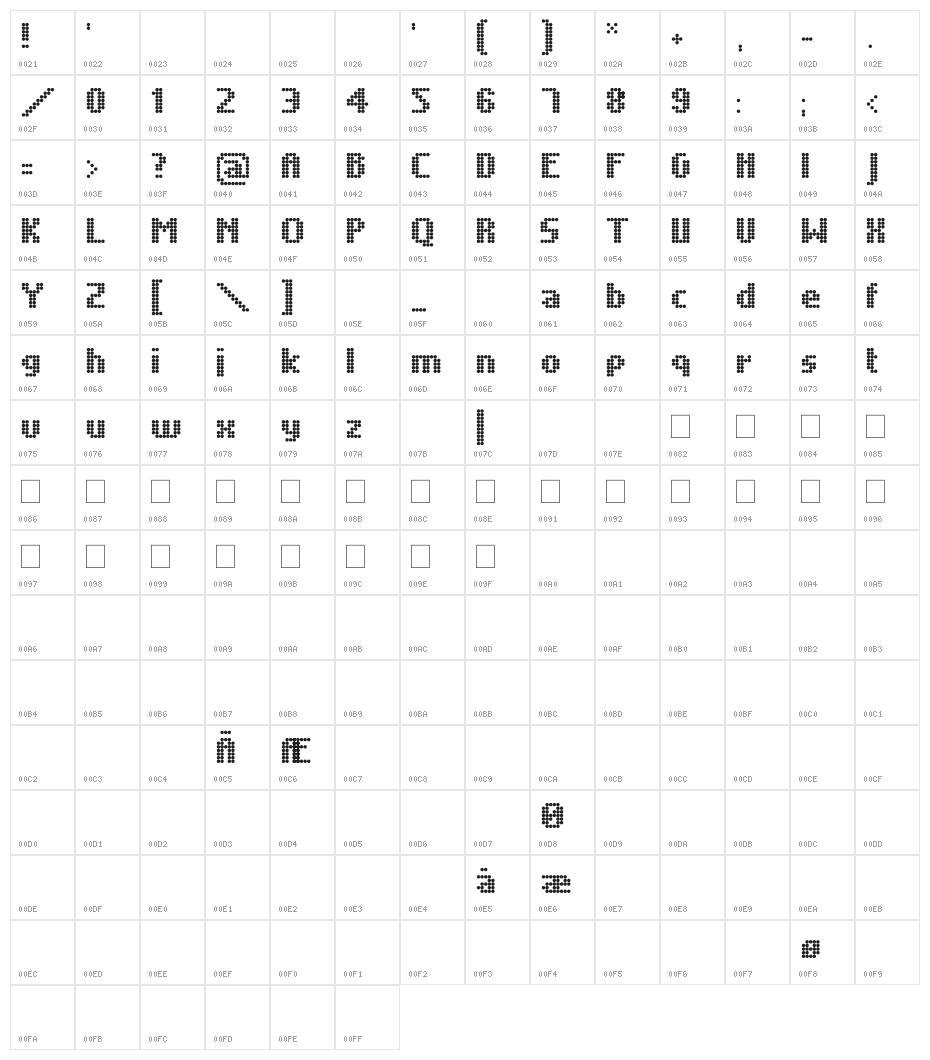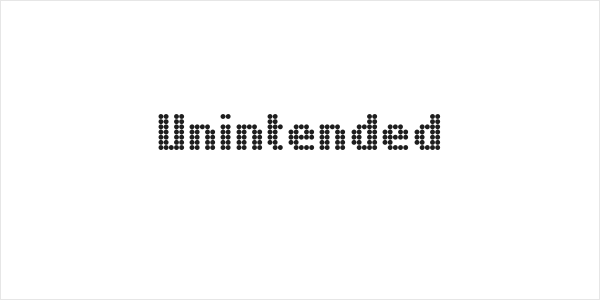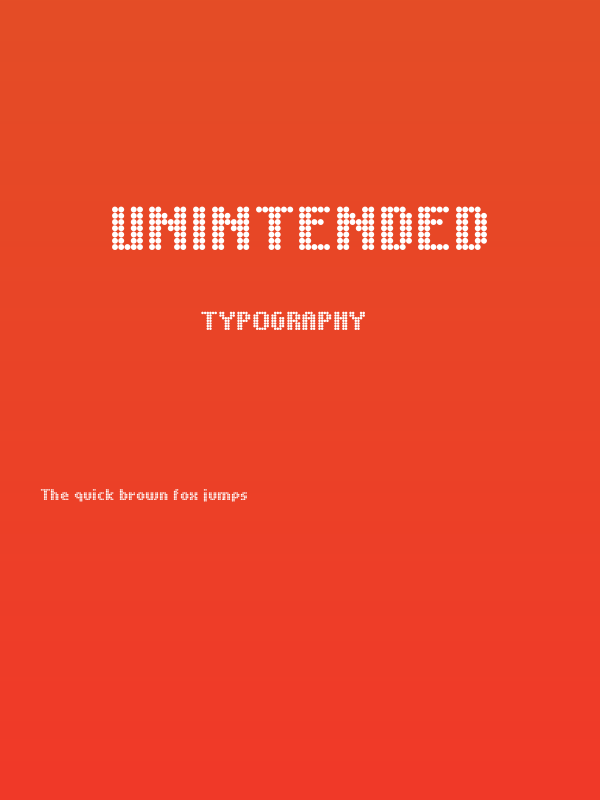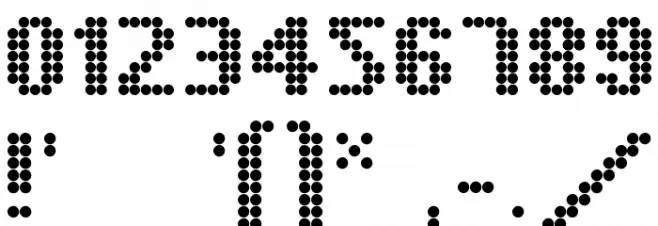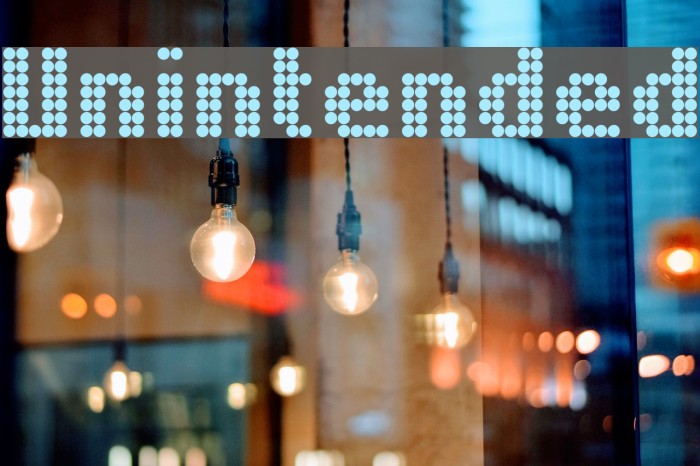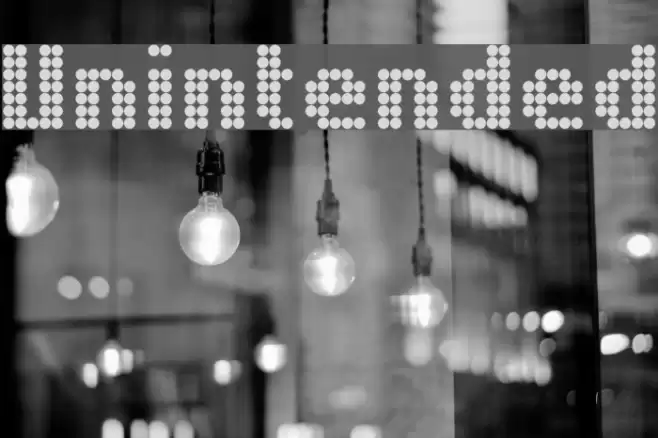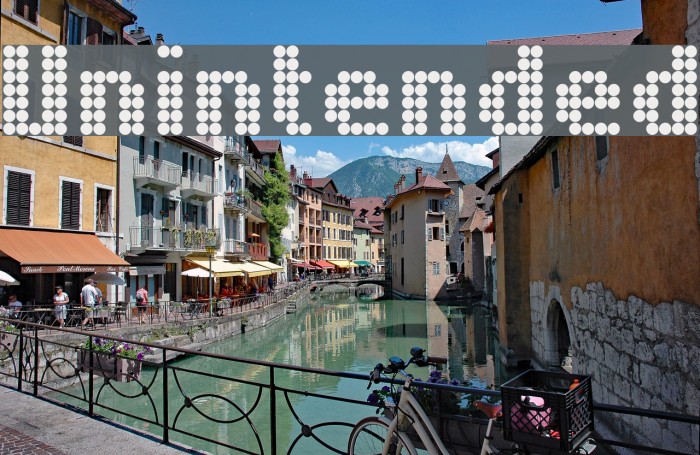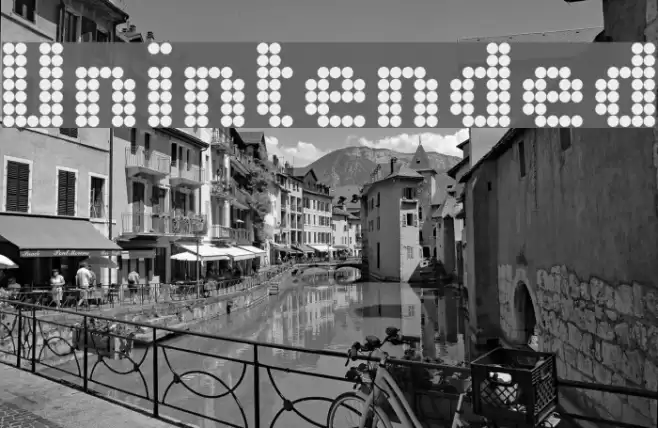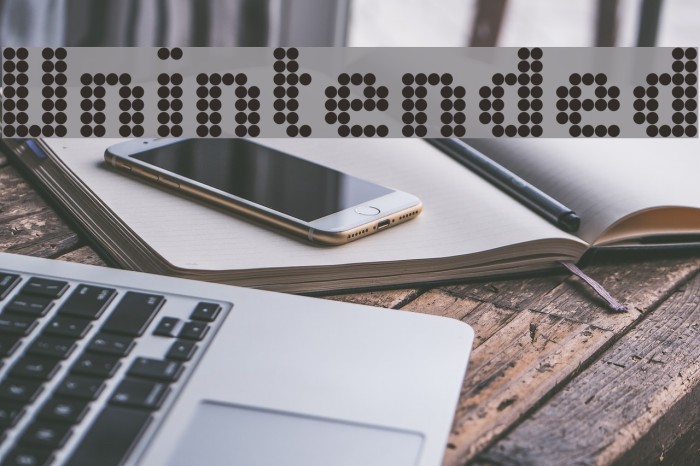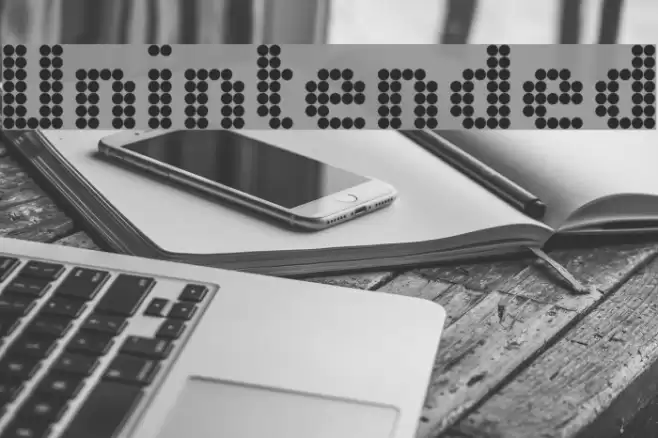
Unintended Font
| Style général | Retro, Digital |
| Projets proposés | Ideal for digital-themed designs, retro video game graphics, tech-related branding, and creative posters. |